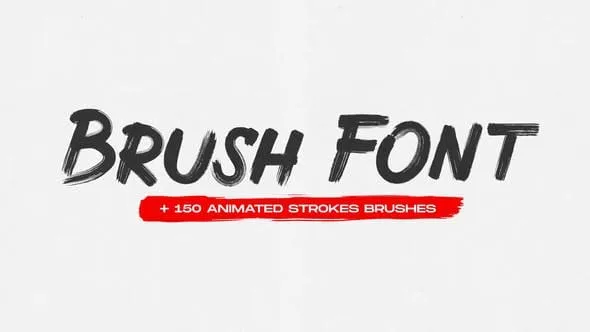
الأبجدية الإنجليزية A-Z / a-z
رموز الرياضيات الأساسية
محرف البرنامج النصي
150 ضربة فرشاة
صناعة يدوية 100٪
English alphabet A-Z/a-z
Basic Math Symbols
Script typefacer
150 Brush Stroke
100% handmade